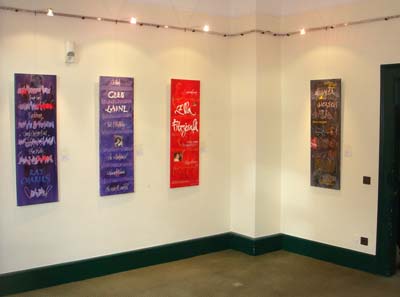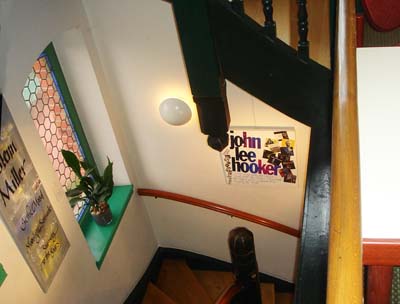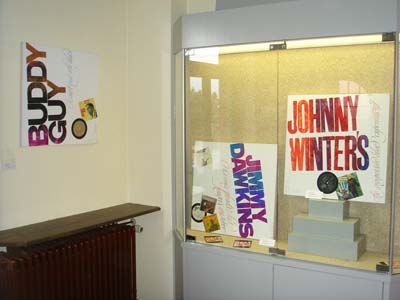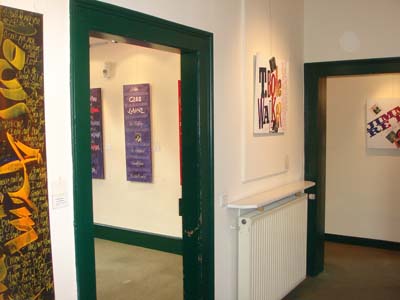
A U S S T E L L U N G
MUSIK WORT MALEREI – Jazz & Blues
Schriftkunst von Katharina Pieper & Jean Larcher
vom 1. April bis 1. Mai 2011
in der Villa Meixner, Brühl/Baden
Einige Einblicke in die Ausstellung:
Eine ungewöhnliche Ausstellung zweier Schriftkünstler kann vom 1. April bis zum 1. Mai in der Villa Meixner angesehen werden. Katharina Pieper (Homburg/Saar) und Jean Larcher (Paris) zeigen kalligrafische Arbeiten, jeder in seiner persönlichen Weise. Beide widmen sich dem Thema „Jazz und Blues“ und wichtigen Künstlern dieser Musikrichtung, quasi als Hommage an Musiker wie B.B. King, Ella Fitzgerald, T-Bone Walker oder Muddy Waters. Während die studierte Designerin Katharina Pieper (Jahrgang 1962) ihren eigenen rhythmisch-malerischen Schriftstil entwickelt hat, arbeitet der Spezialist für exakte und kreative Schriftanwendung Jean Larcher (Jahrgang 1947) eher typografisch. In Acryl-Gouache-Collage-Mischtechniken auf Leinwand verbinden beide Schriftkünstler, die in Fachkreisen eine große internationale Anerkennung besitzen und bereits in St. Petersburg, Korea oder den Vereinigten Arabischen Emiraten ausgestellt haben, Schrift mit Malerei und Grafik mit Kalligrafie. Die Kunst des ausdrucksvollen Schreibens, wie man heute die Kalligrafie treffender bezeichnen könnte, genießt in asiatischen oder orientalischen Ländern höchstes Ansehen, während sie bei uns im lateinischen Schriftenkreis ein Schattendasein führt. Beide Schriftkünstler sind Botschafter eines traditionellen Kulturguts, das sie auch in Kursen und Seminaren sowie Büchern und zahlreichen Publikationen weltweit verbreiten. |